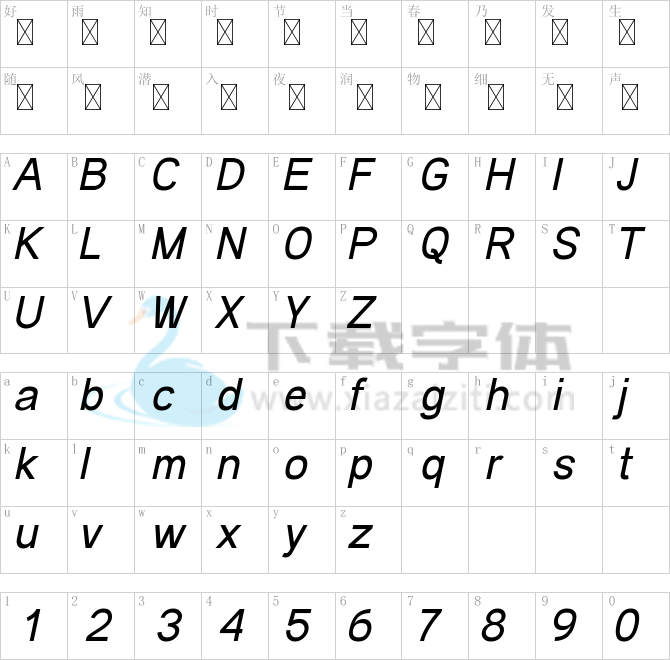
Andala.ttf字体下载,这款字体结构工整、笔画清晰,兼顾美观与易读性,适用于标题、正文、海报、包装、LOGO 等多种场景。字形优雅稳定,风格百搭耐看,适配日常排版与创意设计,让文字呈现更舒适、更具质感。Andala.ttf字体下载一笔一画,皆是细节,以均衡的比例、流畅的线条打造舒适视觉体验,字形端正大气,风格简约现代。无论是商业设计、品牌宣传还是日常排版,都能轻松驾驭,让文字更有格调与力量。Andala.ttf字体下载字体下载。